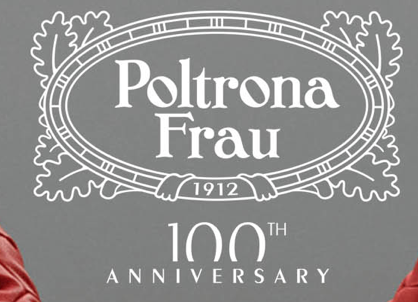
Schrift – Paltrona Frau
kann mir bitte jemand sagen, wie diese Schrift heißt? Hab die auch im neuen Lubalin Buch gesehen, dürft schon etwas älter sein – aber wunderschön. : )
Da die Schrift anscheinend so nur im Logo vorkommt scheint es, für mich, als wäre es eine Eigenkreation. Die Grundlage war wohl eine Windsor und mindestens einer anderen Schrift.